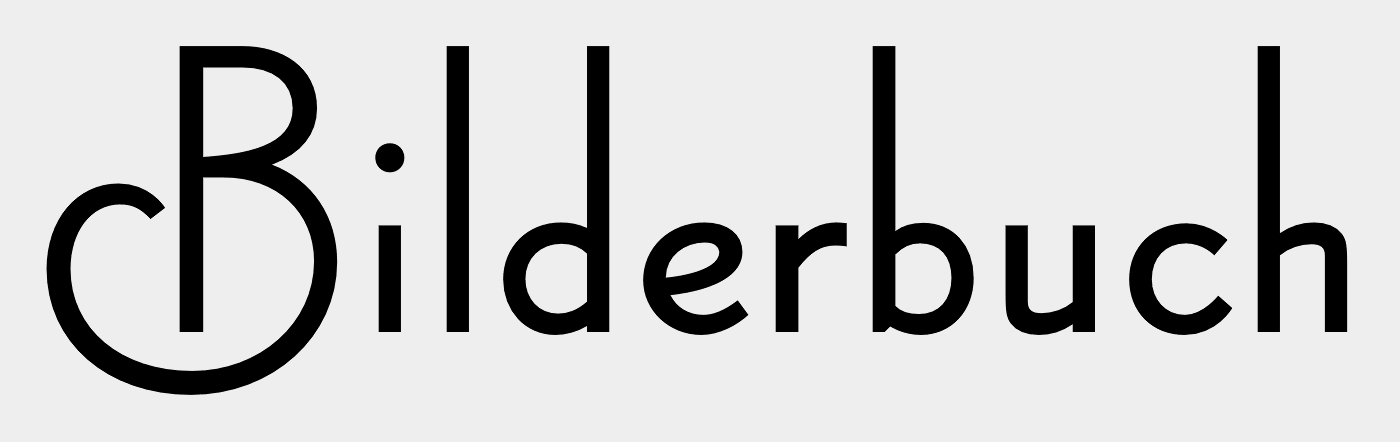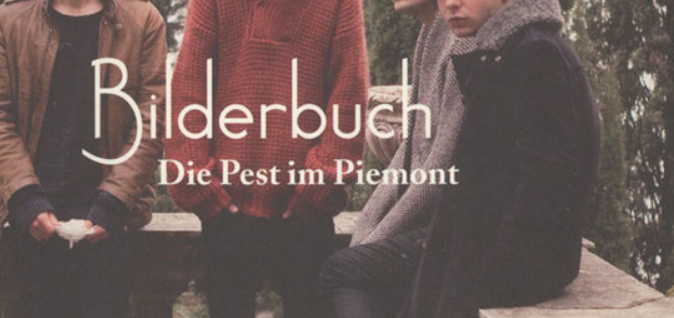
Schrift auf »Bilderbuch«-CD-Cover gesucht
Suche die Schrift, mit der der Bandname auf der Bilderbuch-CD »Die Pest im Piemont« gesetzt wurde.
Mit der Emblema kommt man schon ganz gut hin, aber das B, das r, das h … sind doch ganz anders.
Mittlerweile gefunden – Noir-et-Blanc, ein »Gratisfont« mit spärlichster Glyphenbelegung (z.B. keine Umlaute, keine Akzente). Und auch untauglich für den alltäglichen Praxisgebrauch.
Aber kennt vielleicht jemand eine Alternative, die noch etwas näher am Noir-et-Blanc-»Bilderbuch«-Schriftzug liegt als die Emblema.